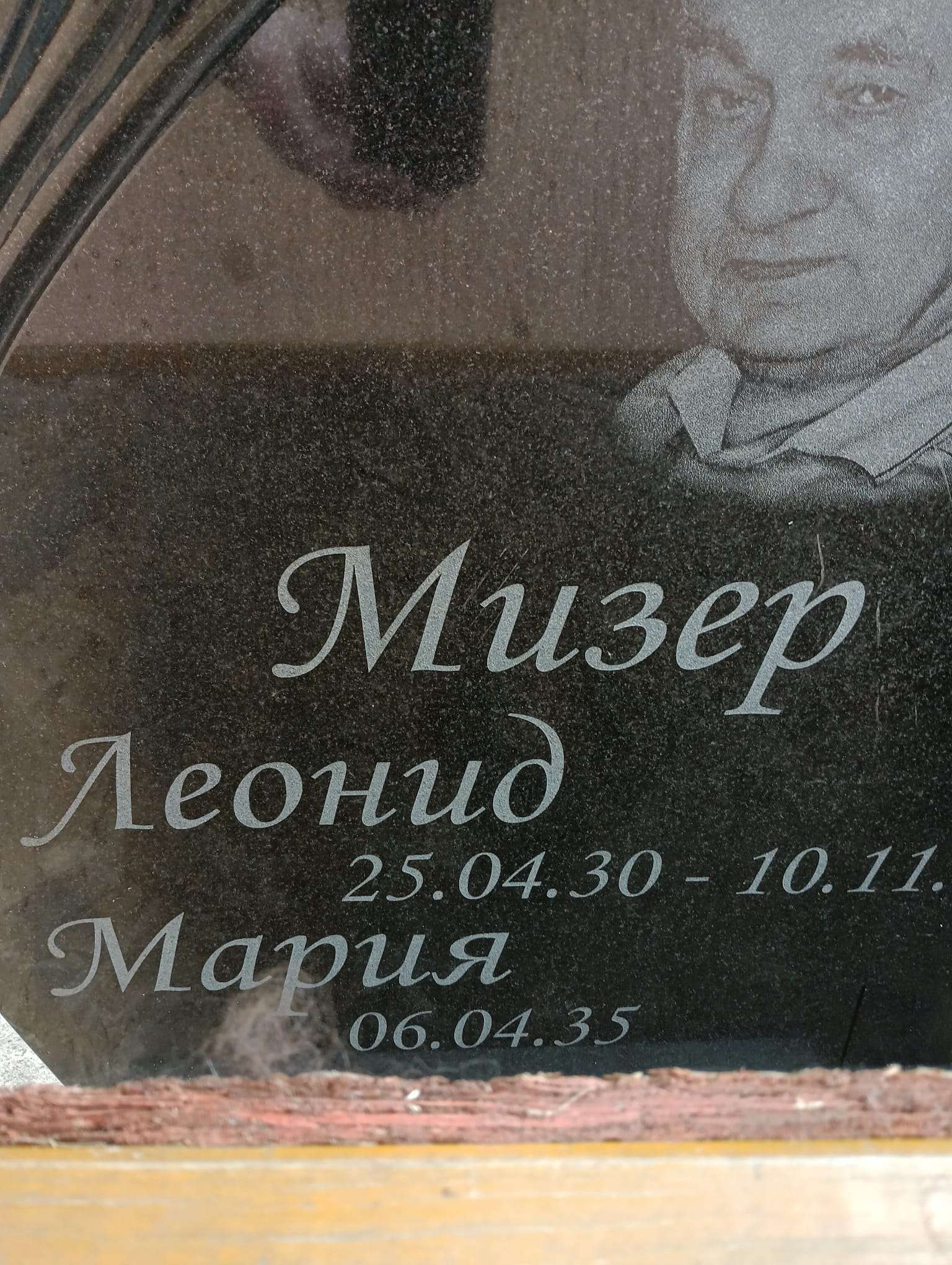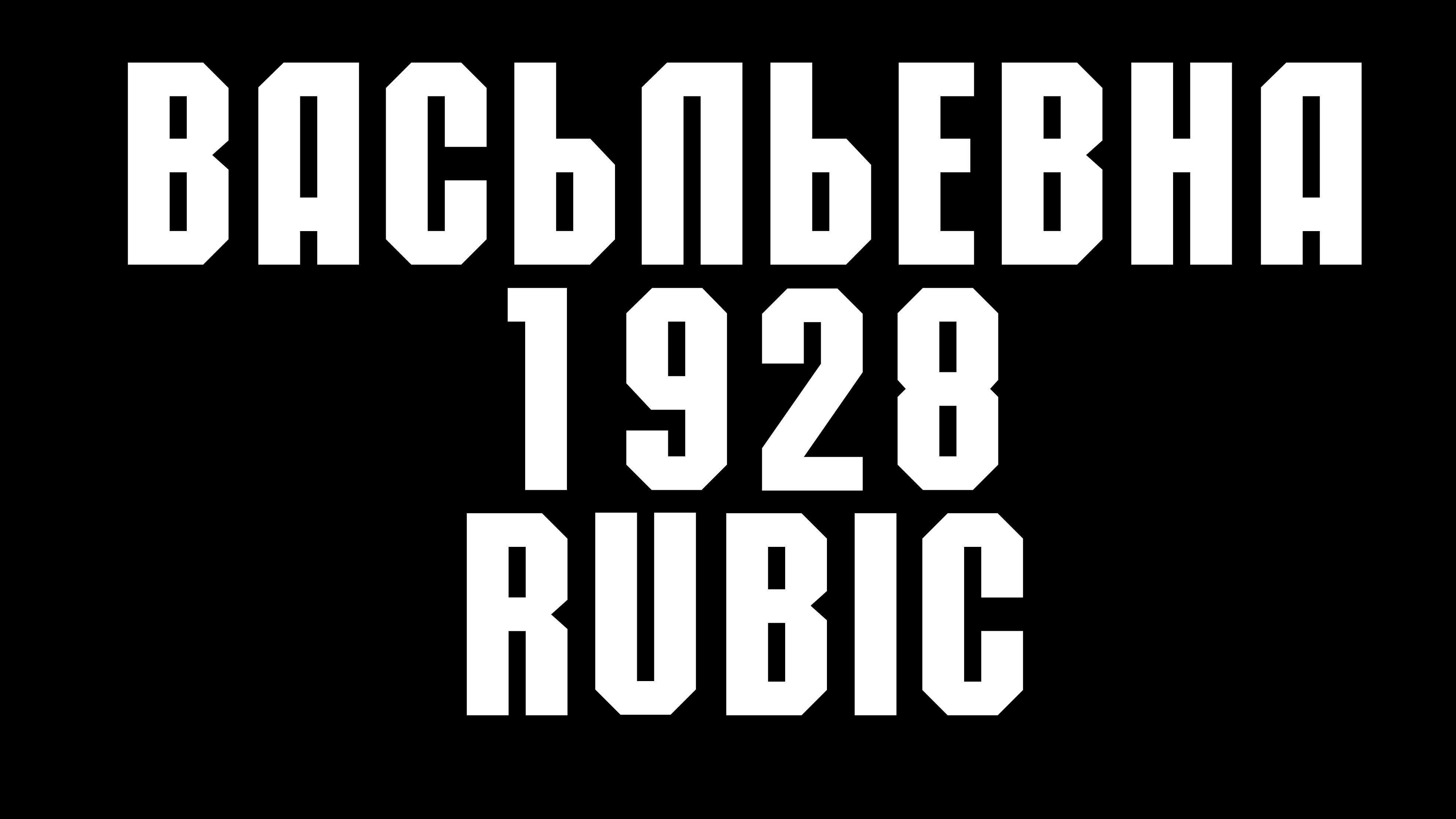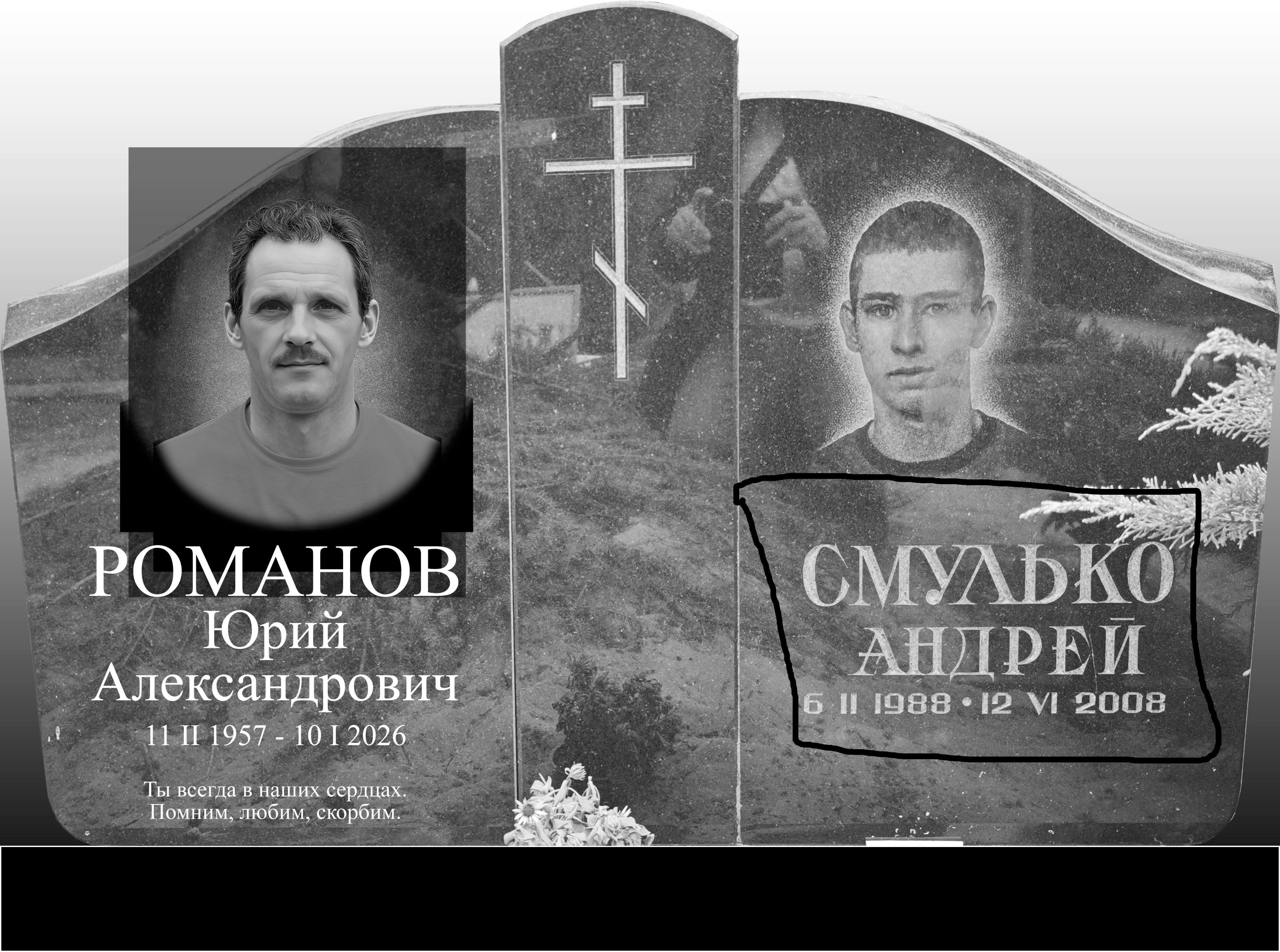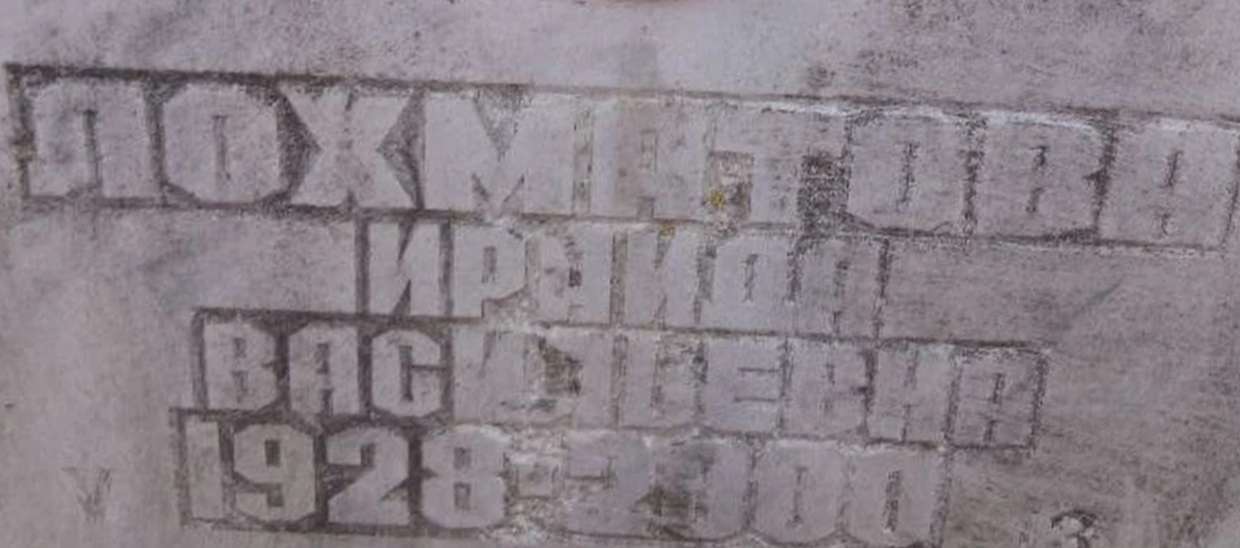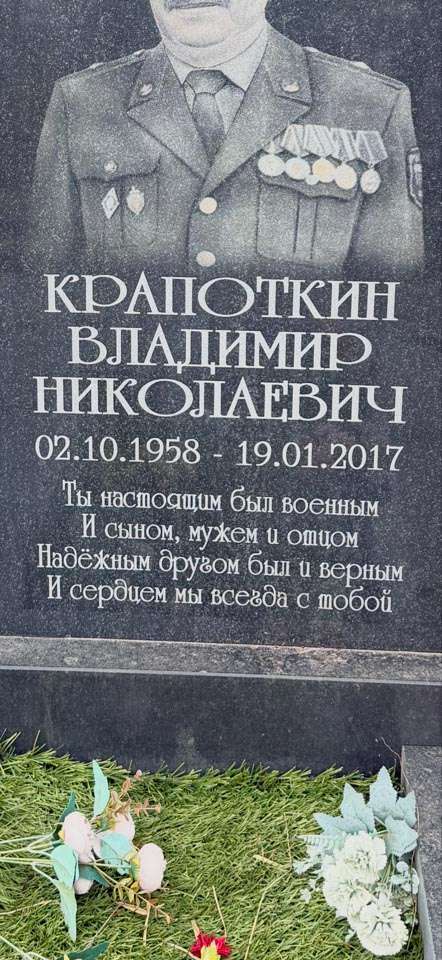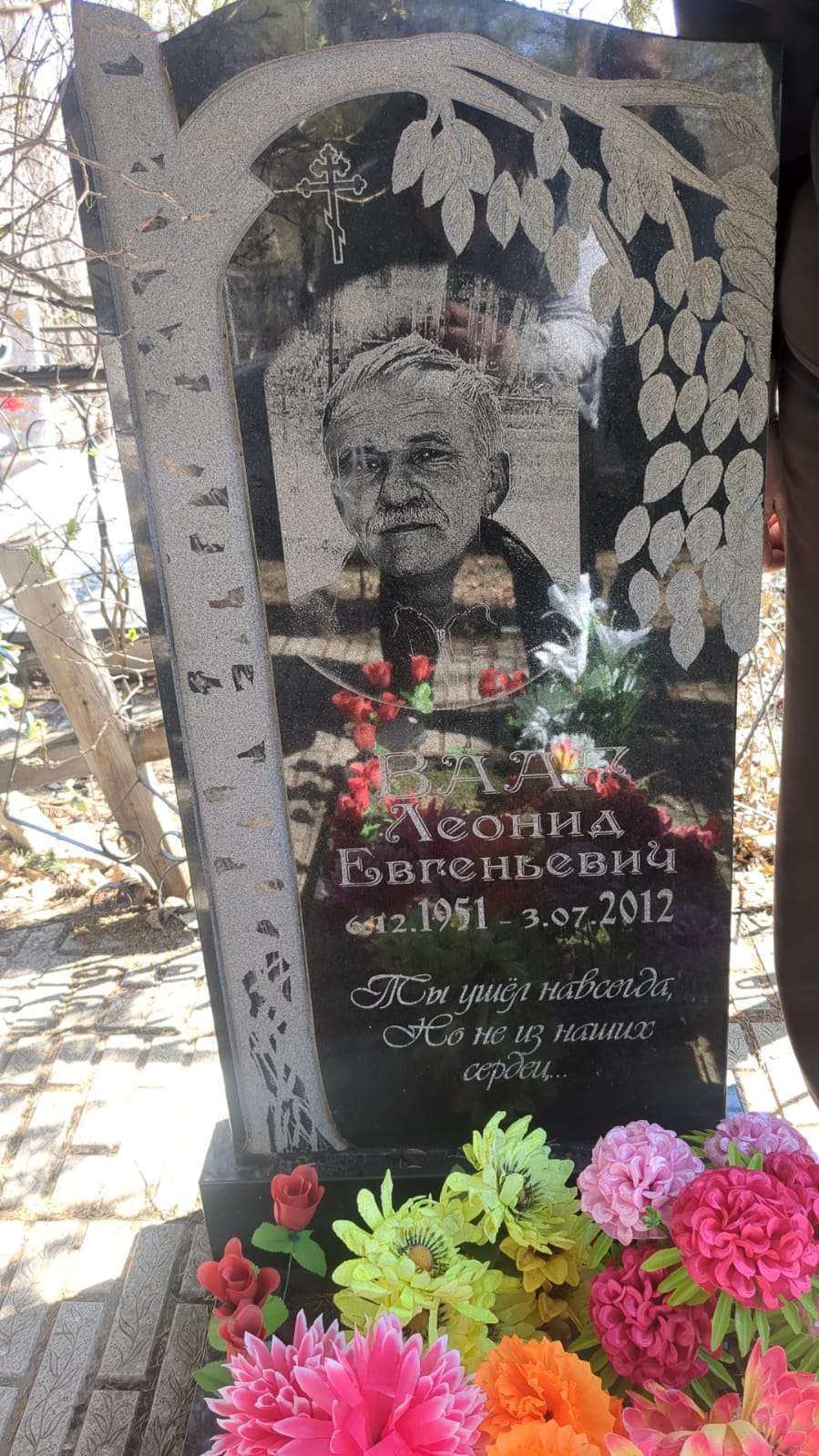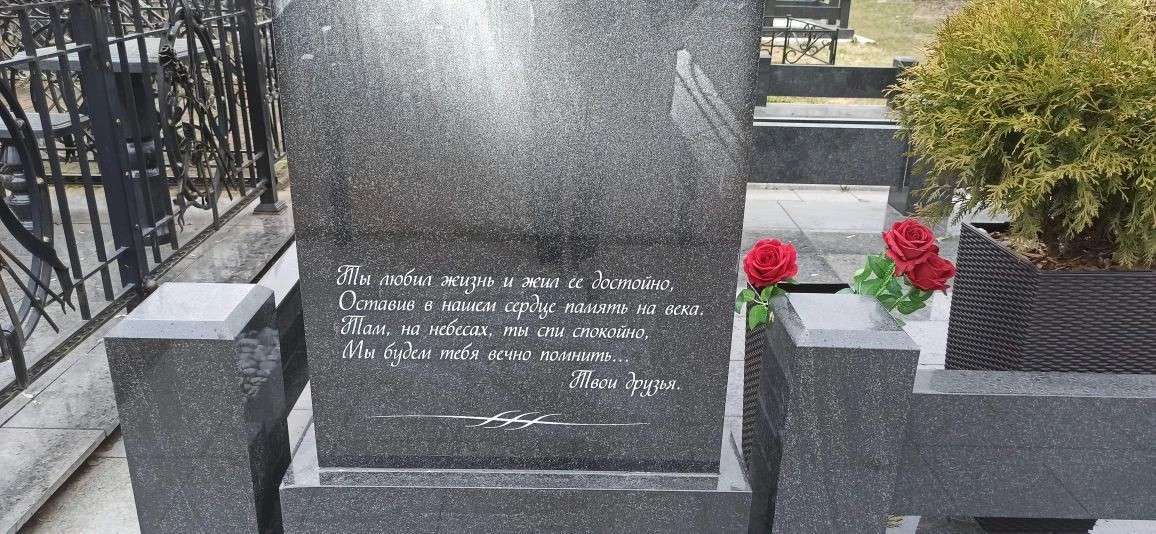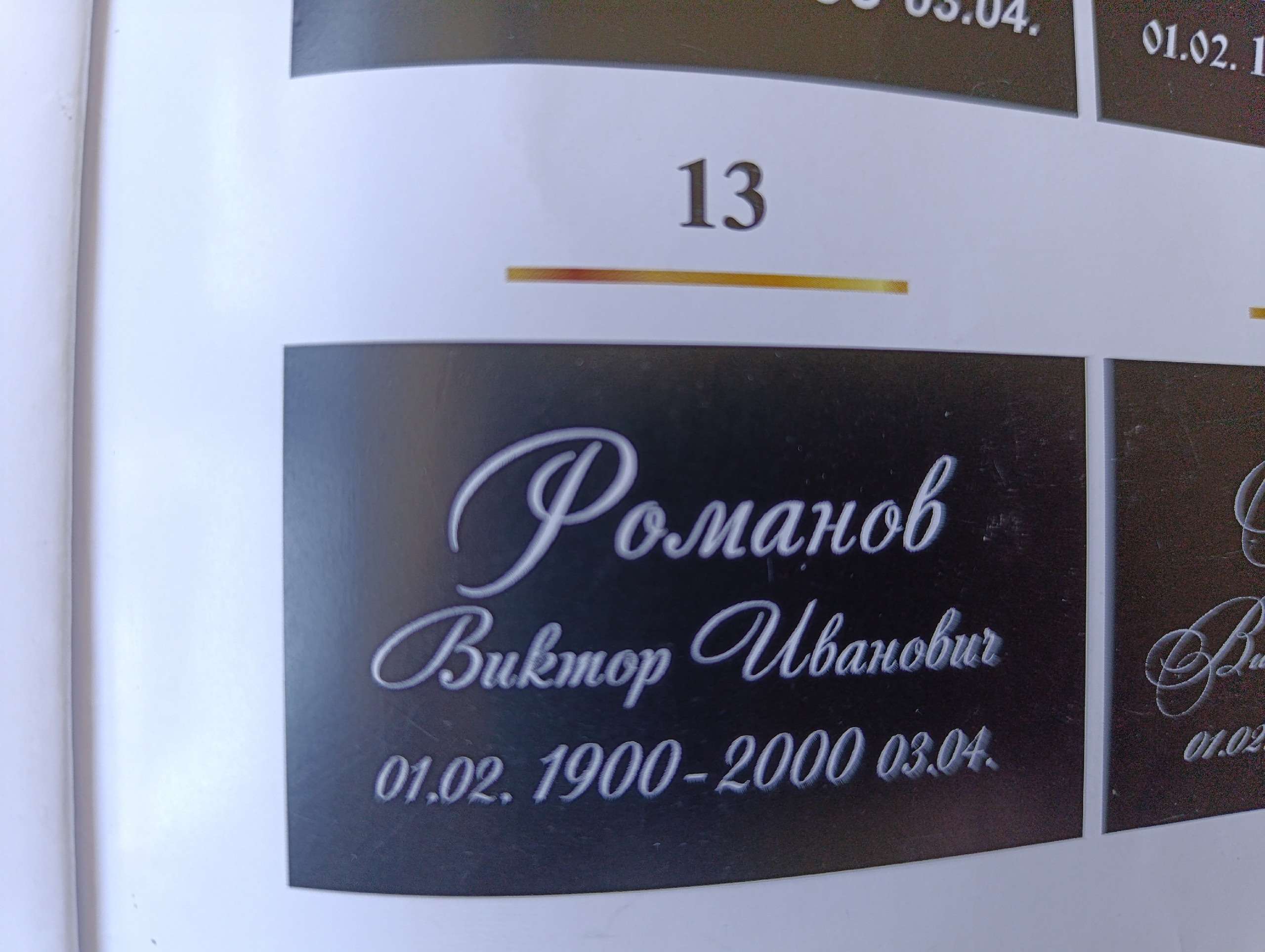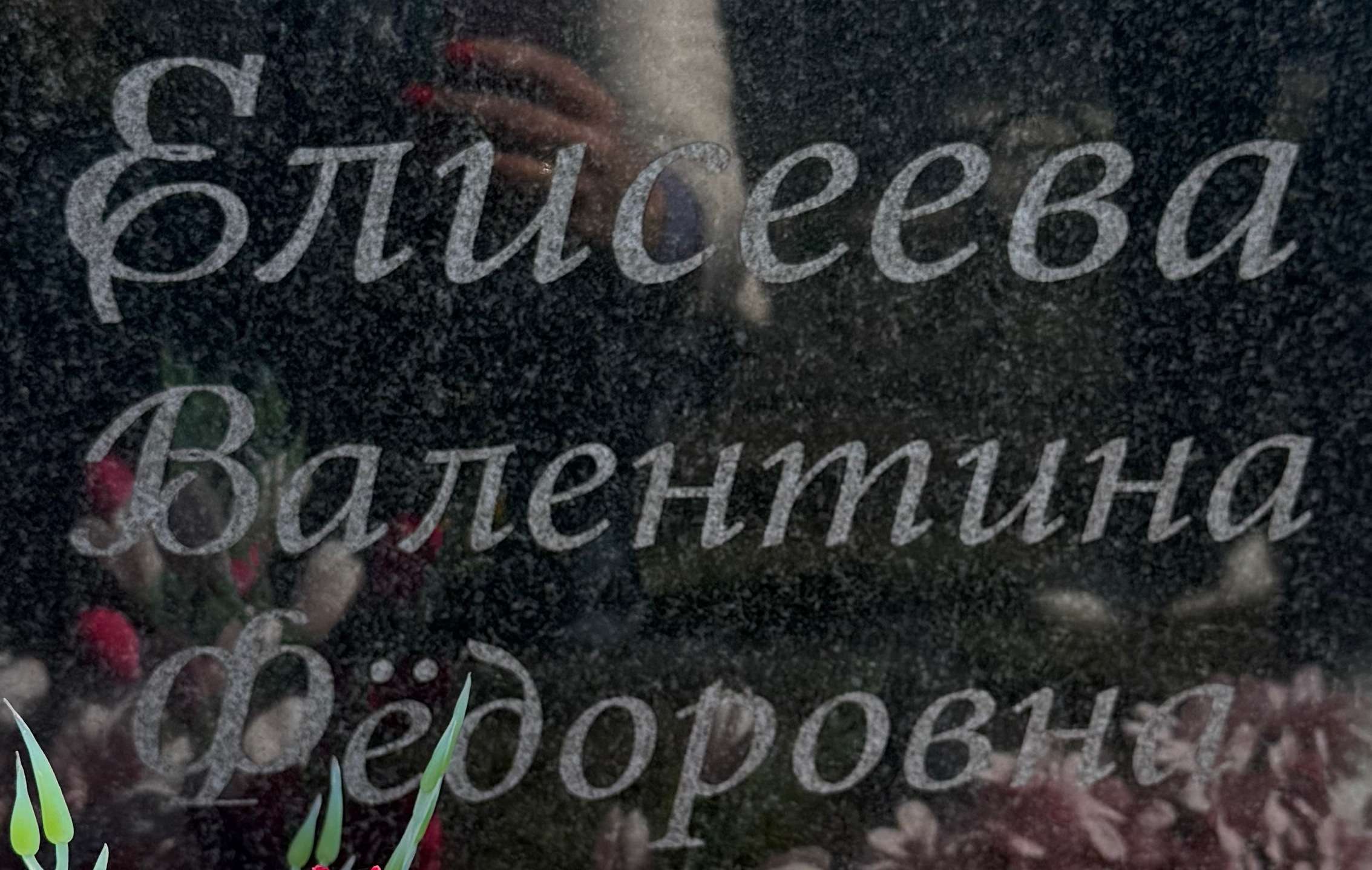
АлександрTv Опубликовано 15 марта Всем доброго времени суток!!! Помогите найти шрифт... Заранее благодарю!!!
hunter007 Опубликовано 15 марта Здравствуйте. Помогите пожалуйста найти шрифты: ФИО, даты и эпитафия. Вроде простые, но подобрать сам не могу
mobil78 Опубликовано 19 апреля Доброго времени суток коллеги! Кто знает что за шрифт?
Kim Опубликовано 21 апреля В 20.04.2026 в 03:19, mobil78 сказал: Доброго времени суток коллеги! Кто знает что за шрифт? a_Romanus
Storn Опубликовано 23 апреля 19 минут назад, aazt сказал: подскажите шрифты пожалуйста эпитафия - VivaldiD GL 1
Виктор П Опубликовано 28 апреля Всем привет, подскажите пожалуйста название шрифта. За ранее спасибо.
Racoon167 Опубликовано 3 мая Здравствуйте. Подскажите название шрифта, пожалуйста, если это возможно!
Storn Опубликовано 3 июня шрифт делал пьяный мастер в ручную шрифт - Zapf Chancery, но заглавную букву "И" в отчестве, он криво стилизовал под это шрифт, в оригинале буква чуть другая
Romeo Опубликовано 11 июня Коллеги,добрый день. помогите разобраться..основной блок вроде Century Schoolbook, цифры вроде Book Antiqua..но что то не ложится на скан ничего.Есть у кого мысли что за шрифты
Romeo Опубликовано 11 июня 5 минут назад, aazt сказал: @Romeo они ? это не TIME NEW ROMAN..видно по букве Л